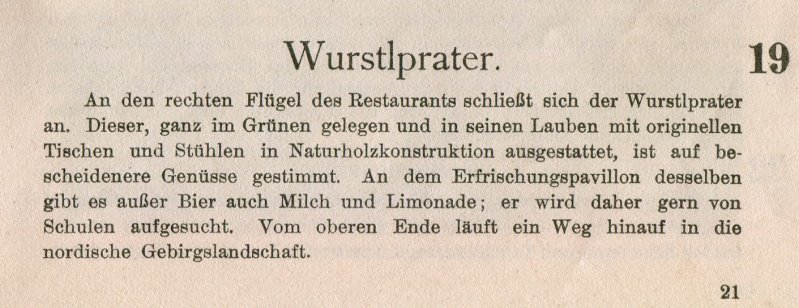
Schriftart aus Heft von 1925
ich bin auf der Suche nach der Bezeichnung für diese Schriftart, hat jemand eine Idee? :)
Es handelt sich um zwei verschiedene Schriftarten. Die Überschrift „Wurstlprater“ ist aus einer „Old-Style“-Schrift gesetzt, der Text darunter aus einer klassizistischen Antiqua schottischen Types. Die Zahlen sind auch aus klassizistischen Schriften gesetzt. In folgendem Gespräch habe ich schon einmal etwas zu diesen Schriftarten geschrieben; Du findest dort auch Beispiele: